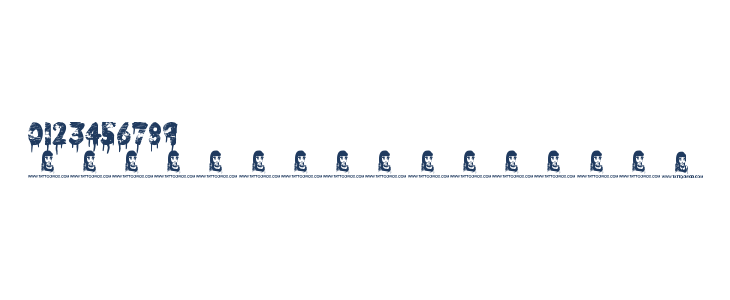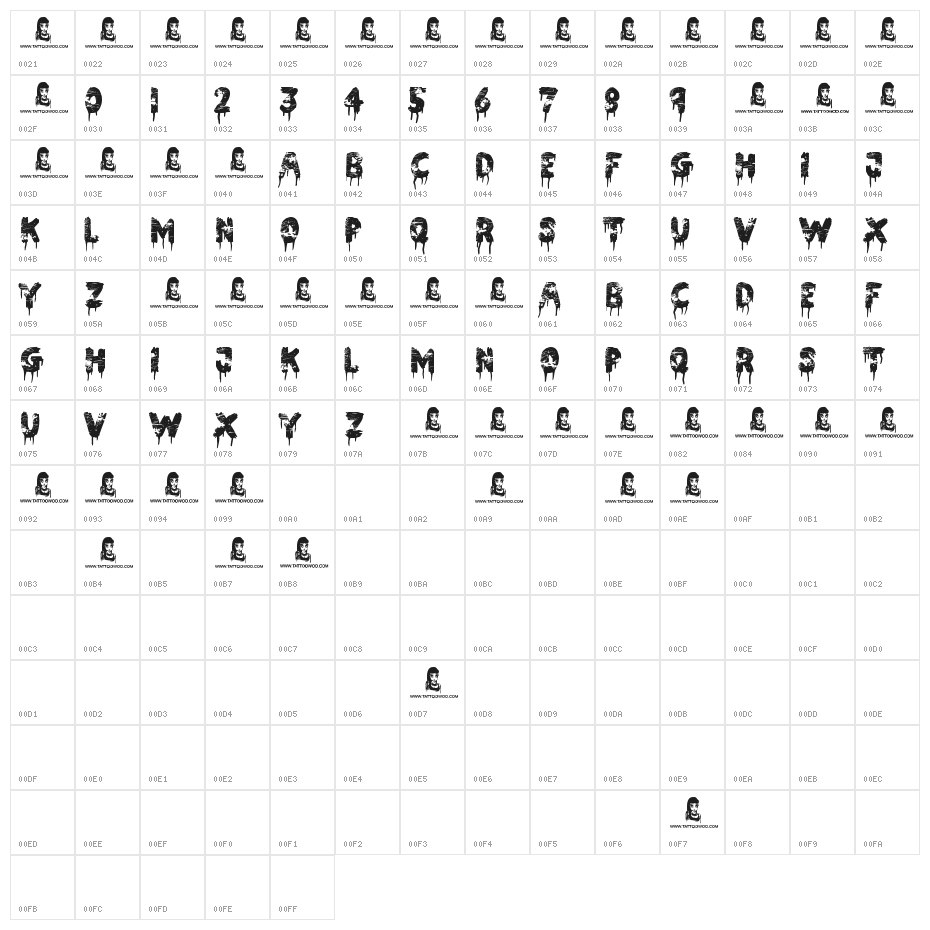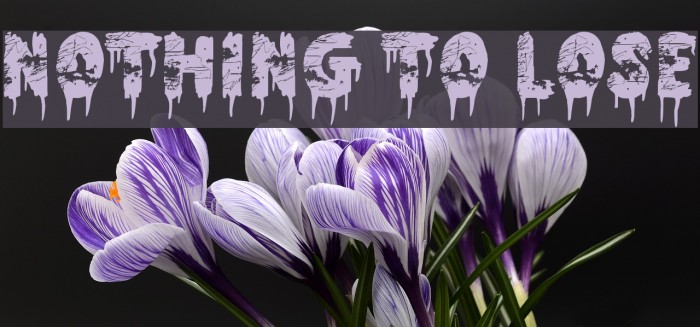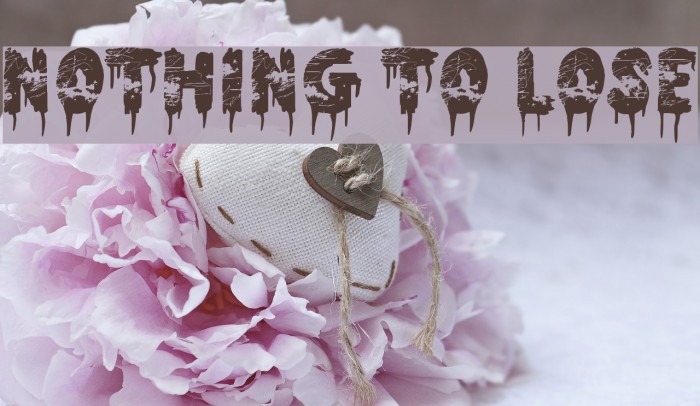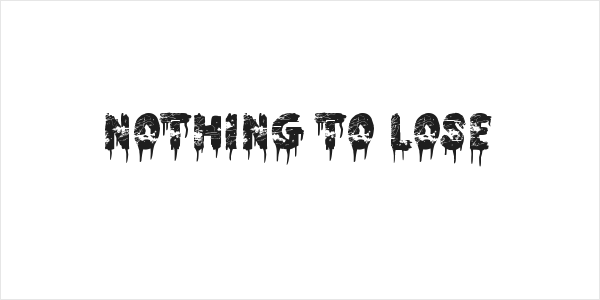
Nothing To Lose Font
| Vorgeschlagene Projekte | Ideal for horror-themed designs, music album covers, posters, and any project needing a bold, edgy look. |